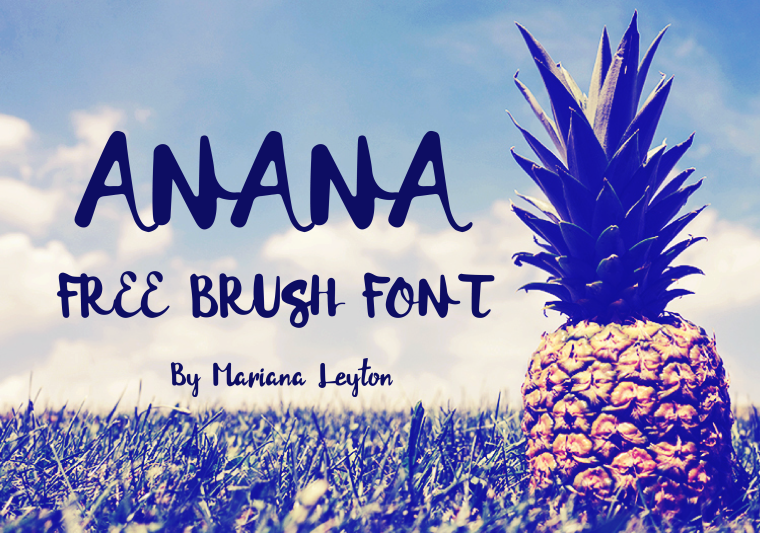
Sejak awal tahun 2016 sampai akhir tahun banyak sekali font yang dibagikan secara gratis, mulai dari serif font, script, brush, handletter dan lainnya. Pada kesempatan kali ini Jago Desain telah mengumpulkan sebanyak 20 font script terbaik pada tahun 2016 yang bisa di unduh secara gratis legal untuk penggunaan personal (pribadi) maupun komersial.
Semua script font ini dikumpulkan dari berbagai sumber blog yang terpercaya, semua font sangat cocok untuk desainer grafis baik untuk desain logo, poster, atau desain lain. 20 script font ini di review dan dipilih berdasarkan keunikan, lisensi yang diberikan dan banyaknya glyphs yang tersedia dari font tersebut.
Anana Brush Font
Noelan Caligraphy Typeface
Memiliki desain yang rapi dan modern, Noelan sangat cocok bagi anda yang senang membuat tipografi yang bisa diaplikasikan untuk kaos, poster atau lainnya dan pastinya gratis untuk personal dan komersial.